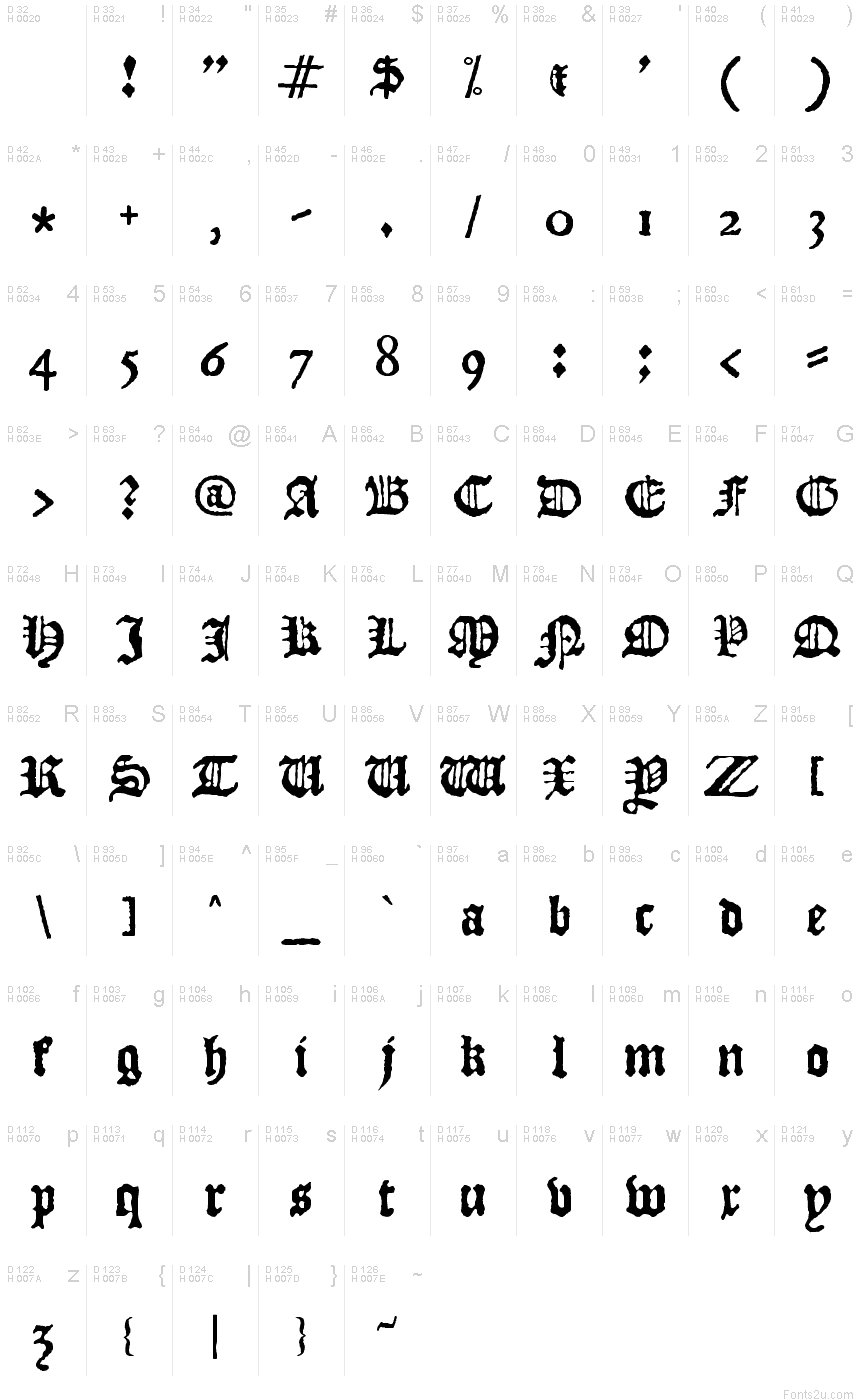
JSL Blackletter autorstwa Jeffreya S. Lee to darmowy, średniowieczny krój pisma typu blackletter. Jego atramentowe, nieregularne pociągnięcia i gęsta faktura sprawiają wrażenie, jakby zostały przeniesione prosto ze starego pergaminu, nadając każdemu słowu rytualny, ręcznie kreślony ciężar. Litery są zwarte i dramatyczne, a poszarpane krawędzie tworzą surowy, historyczny klimat, daleki od czystych i wygładzonych form.
Dzięki JSL Blackletter nadasz natychmiastową powagę okładkom książek fantasy, logotypom zespołów metalowych, tytułom gier, okultystycznym fanzinom, etykietom piw rzemieślniczych czy plakatom z festynów renesansowych. Ten darmowy font najlepiej sprawdza się w większych rozmiarach, gdzie jego chropowate kontury i ciężki rytm mogą w pełni wybrzmieć. W przypadku tekstów pomocniczych zestaw go z prostym, nowoczesnym krojem bezszeryfowym, aby zachować czytelność, jednocześnie pozwalając JSL Blackletter grać pierwsze skrzypce.